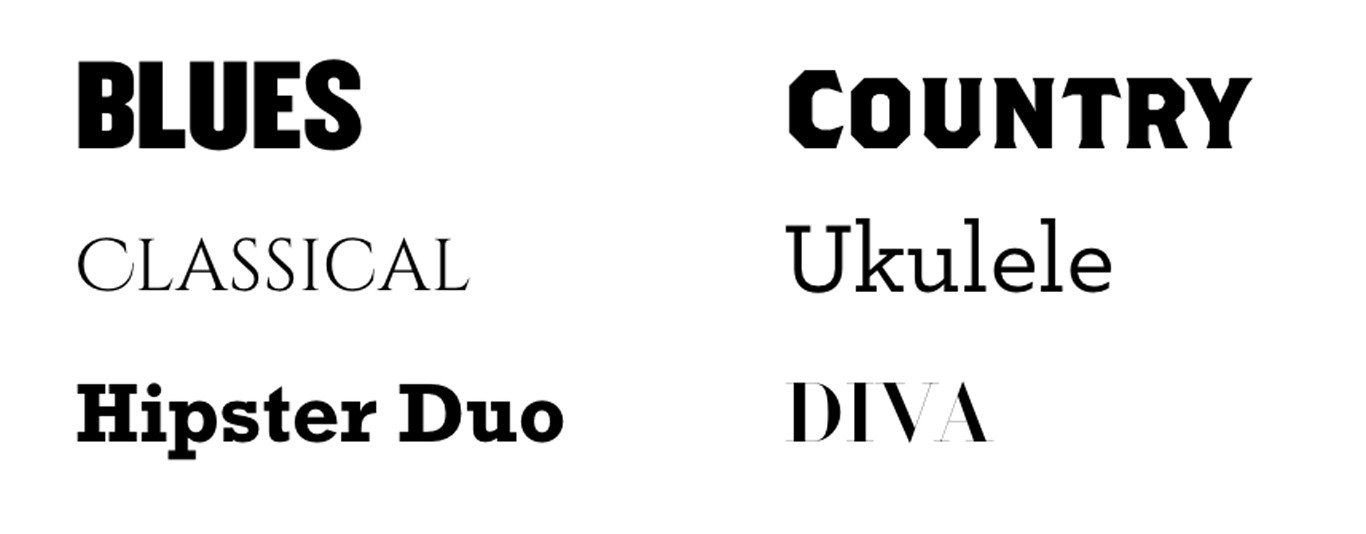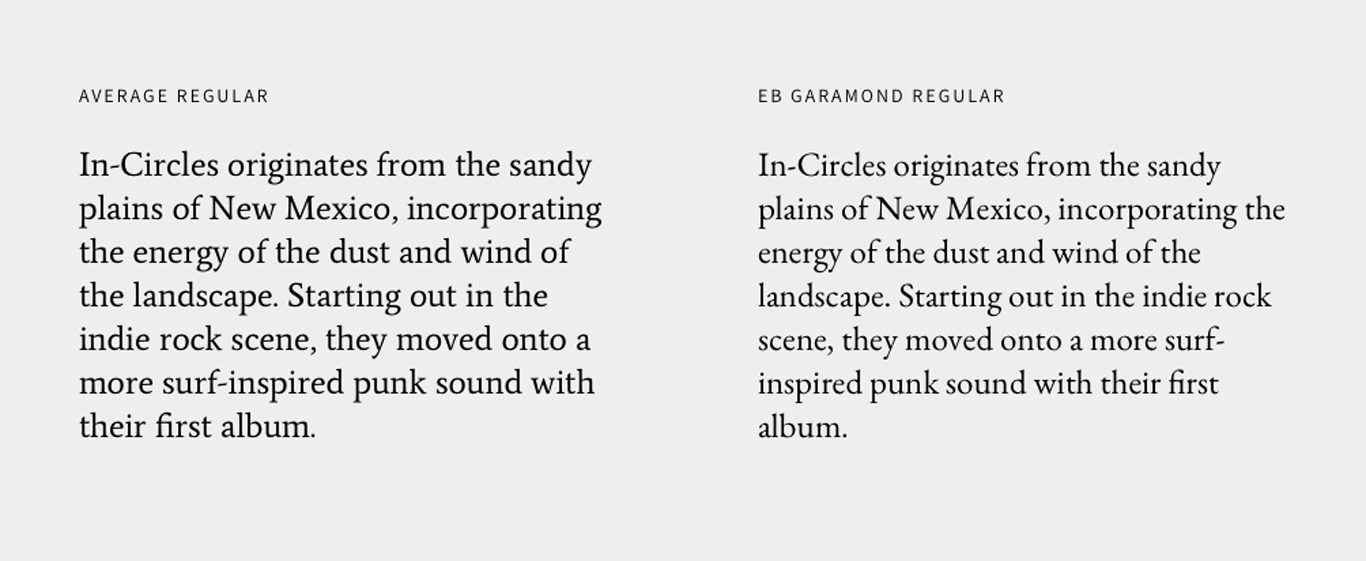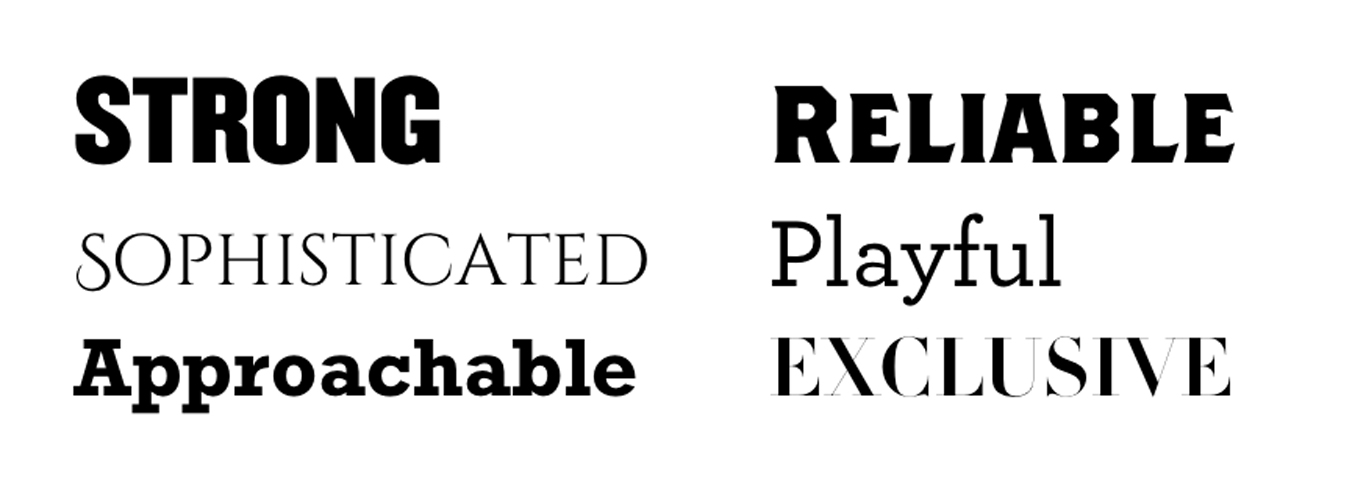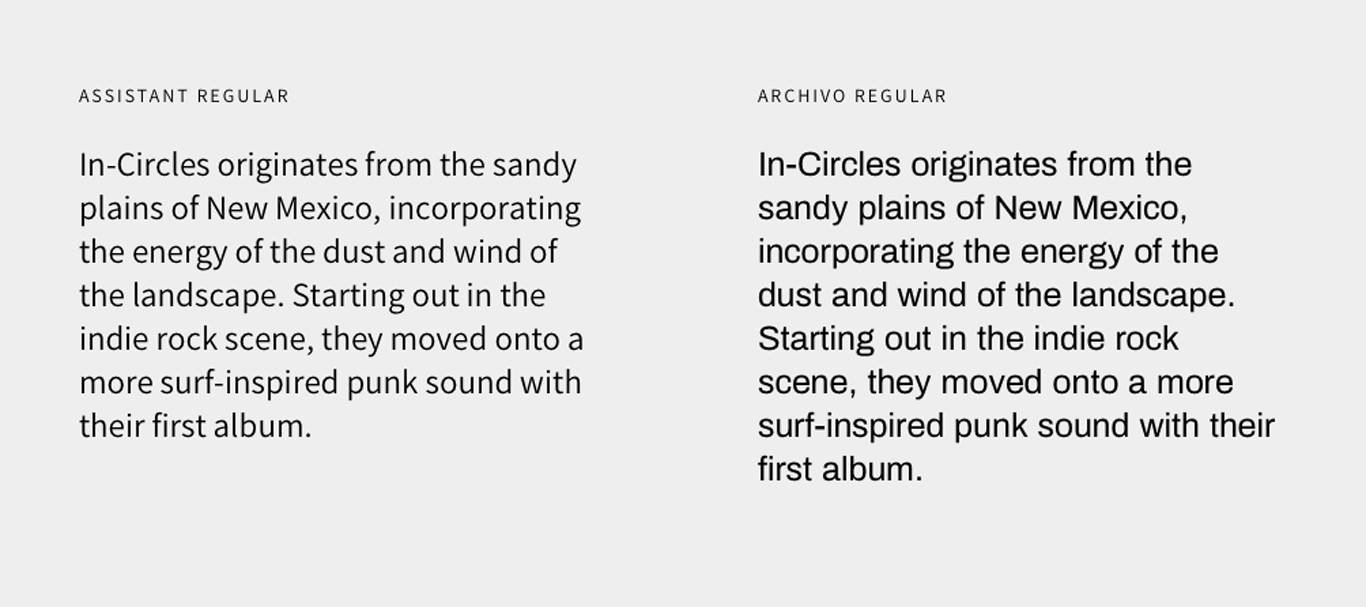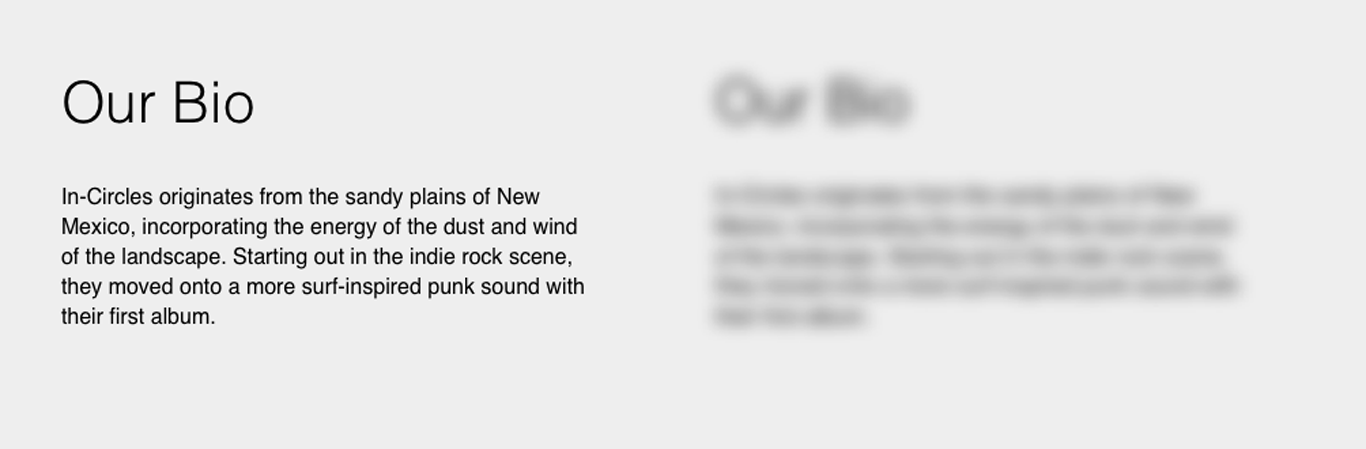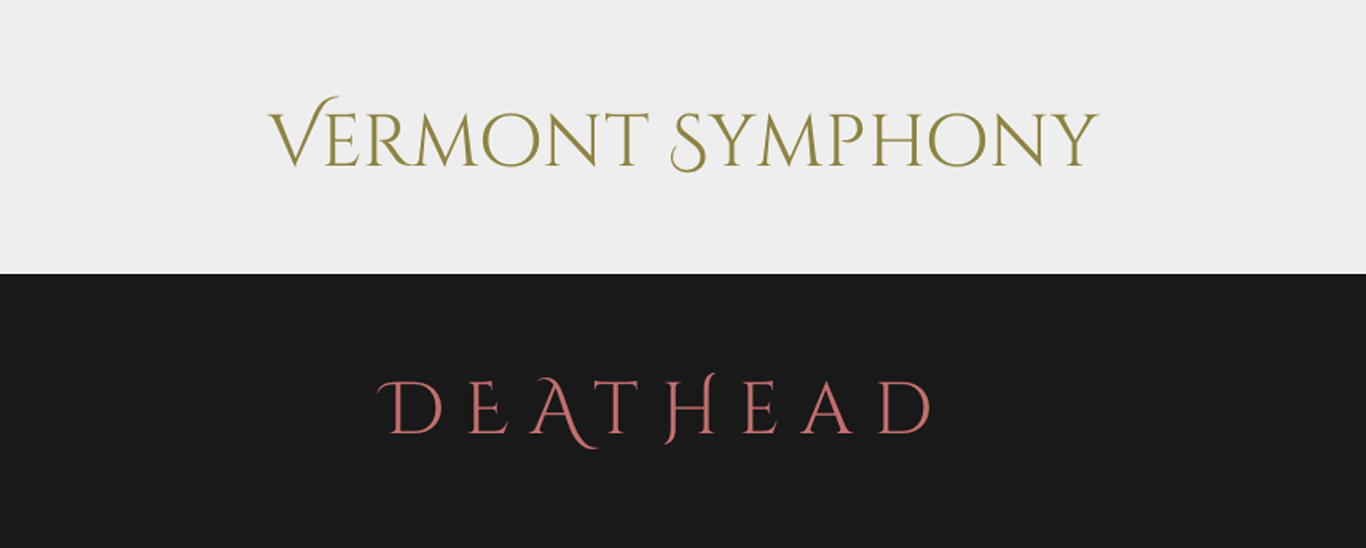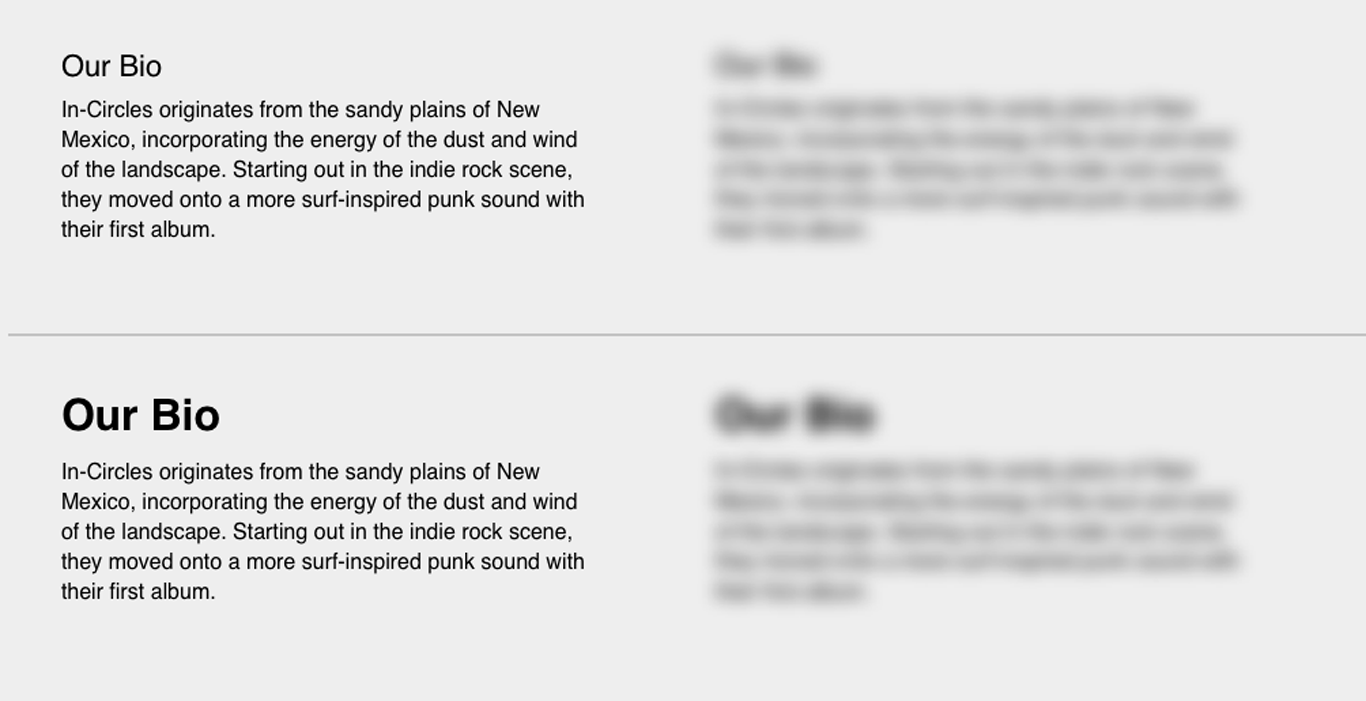
バンドのWebサイトのフォントを選択する方法
公開: 2022-06-03写真は千の言葉の価値がありますが、時にはそれらの言葉についても慎重に考える必要があります。 適切なフォントを選択すると、Webサイトを実際に結び付けて、まとまりのあるルックアンドフィールを実現できます。 それはあなたの全体的なブランディングにおける重要な要素です。
現在、高品質のフォントが豊富にあります。 では、この膨大なオプションを使用して、バンドのWebサイトに適したフォントをどのように選択しますか?
トーンがすべてです
バンドのWebサイト、またはバンドのロゴのフォントを選択するときは、提示したいトーンを実際に考慮する必要があります。 トーンは、「これを見たり、聞いたり、体験したりするときに、どのように感じますか?」という別の言い方です。
以下の例では、いくつかの形容詞を適切なフォントと一致させようとしました。 フォントが大胆で頑丈、そしてコンパクトであれば、強度や信頼性さえも伝えることができます。
洗練された表現は、薄くエレガントなセリフのフォントで表すことができます。 遊び心のある例では、少し気まぐれな感じを与える丸みを帯びた端子があります。
それでは、これらの形容詞のいくつかをいくつかの音楽用語やジャンルに一致させてみましょう。
したがって、これらのほとんどは形容詞によく合います。 「Sophisticated」はクラシックのジャンル、「Playful」は楽しいウクレレ、「Approachable」はかわいいヒップスターデュオ、「Exclusive」フォントは今では歌姫です。
ブルースとカントリーは、それぞれ「Strong」と「Reliable」のフォントを採用しています。 これらのジャンルに必ずしも形容詞を使用するかどうかはわかりませんが、ある程度は機能します。
うまく機能しているのは、それらの書体の歴史です。 「Strong」コンパクトフォントは、ブルースアーティストの初期のポスターデザインにそのフォントが表示される可能性がある特定の時代のものです。
私たちの国のフォントは、世紀の変わり目に見られるかもしれない木版画のフォントであり、それを初期の西部アメリカと関連付けるかもしれません。 したがって、この場合、トーンは履歴によって決定されます。
状況に応じたトーン
上記の「洗練された」例では、NatanaelGamaのフリーフォントCinzelを使用しました。 FontSquirrelは、フォントを次のように記述します。
「シンゼルは、1世紀のローマの碑文に着想を得た書体であり、古典的なプロポーションに基づいています。」
シンゼルは初期のローマの彫刻に触発されたため、キャラクターは彼らに特定の感触を持っています。 したがって、このフォントが交響楽団やクラシックアーティストに使用されていることが簡単にわかります。
しかし、カーニング(文字間のスペース)を開くとすぐに、黒の背景に赤にすると、かなりフィットする金属のロゴができます。
なぜこれが機能するのですか? さて、ローマの彫刻には、鋭い点に向かって先細りになるいくつかの本当に興味深いセリフもあります。 また、このフォントは彫刻に基づいているので、墓石に見られるフォントに少し似ていると思います。 墓石よりも金属は何ですか?
これはすべてのフォントで機能するわけではありませんが、ごくわずかな変更でフォントの色調が変わる場合があることを示したいと思いました。
見出しを設定する
したがって、フォントの選択のトーンが決まったら、それらがバンドのWebサイトとの関連で機能することを確認する必要があります。 フォントをペアリングするときにコンテンツが読みやすいように設定されていることを確認するための簡単なヒントを次に示します。
コントラストの重要性
タイポグラフィとフォントのペアリングの重要な側面の1つは、フォントの選択の間に十分なコントラストを示すことです。これにより、読者はサイトを簡単にスキャンして、コンテンツの始まりと終わりを見つけることができます。
以下の例の上部には、見出しとしてかなり小さいフォントサイズがあり、その下の本文のコピーと同じ重みがあります。
分離すると、実際にはそれほど悪くはありません。 しかし、私がファインアートのトレーニングから得た素晴らしいデザイナーのトリックは、このコンボが機能するかどうかを実際に確認するために目をぼかすことです。
目をぼかすと、上の例の本文のコピーに見出しがにじんでいることがはっきりとわかります。 これがコンテンツの大きなページにあり、特定のコンテンツを探すためにスキャンしていた場合、見出しが消えてしまうため、探していたものを見つけるのは非常に困難です。
下部では、見出しを大きく太字に調整しました。これにより、ぼやけたときに見出しと本文のコピーをはっきりと識別できます。
太字フォントを使用せずにコントラストを作成することもできます。 この例では、薄いサンセリフがありますが、サイズを大きくしてその下に空白を開いたため、ボディコンテンツが始まる場所の始まりを明確に定義しています。
ボディフォントの選択
コントラストを作成する方法と見出しフォントで何を探すかがわかったので、本文フォントを見てみましょう。 本文フォントはサイトの大部分を構成するテキストの段落であるため、私は通常、表示フォントのような間抜けなもの、場合によってはほとんどのセリフを避けます。
あなたの体のフォントは主力であり、簡単に読む必要があります。 また、このフォントは読みやすくする必要がありますが、音色が伝わらないわけではありません。 以下の例では、2つの非常に異なるサンセリフフォントがありますが、どちらも同じように読みやすくなっています。
左側のアシスタントは、私にははるかに親しみやすくフレンドリーに見えます。 一方、Archivoは少し厚く、構造が少し硬めです。 すべての小文字の幅は同じで、フォントのトーンが少し機械的に見えます。
セリフフォントも同じです。 これらの2つの例は、小さいサイズでも非常に読みやすくなっていますが、トーンが異なります。 ガラモンドは大文字と小文字の間で高さのバリエーションが多く、私にはより文学的で際立った感じを伝えます。 トーンは異なりますが、どちらも非常に読みやすいです。